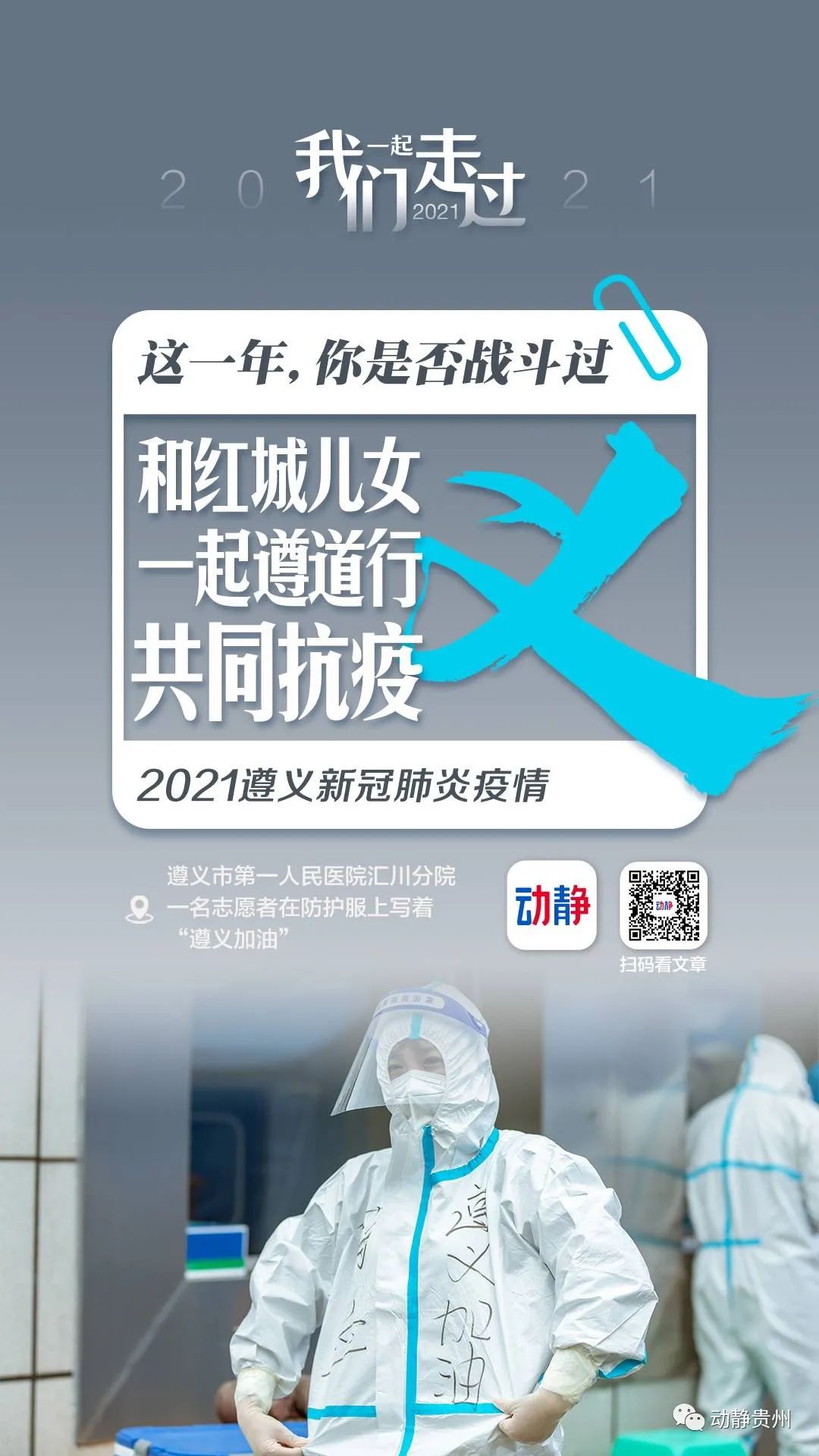
方正字汇-冉黑
冉鹏奇
方正字汇-冉黑是设计师冉鹏奇的首款字体,字体灵感源自作者的梦境。这款字体整体几何感十足,笔画造型刚柔并济,撇捺挺拔有力,转折处用倒角处理,让字体富有亲和力。口字相关字形右下方用切角加倒角处理,让字体的直观感受更加灵动不呆板。可广泛用于品牌logo、包装、平面kv、杂志标题、宣传标语等,具有良好的商业价值。 作者冉鹏奇,字体发烧友,Z时代95后的河北邯郸人。目前任职于星驰广告,担任御用字体设计师及助理美术指导。擅长品牌设计与字体设计,服务于天猫、淘宝、爱慕、TCL、智联招聘、十月结晶、横琴人寿、经开智控等众多著名品牌。在公司任职期间作者全权负责公司所产出的字体设计,积累了丰富的字体设计经验。另外也利用业余时间,凭借自己的热爱开创了一系列字体。